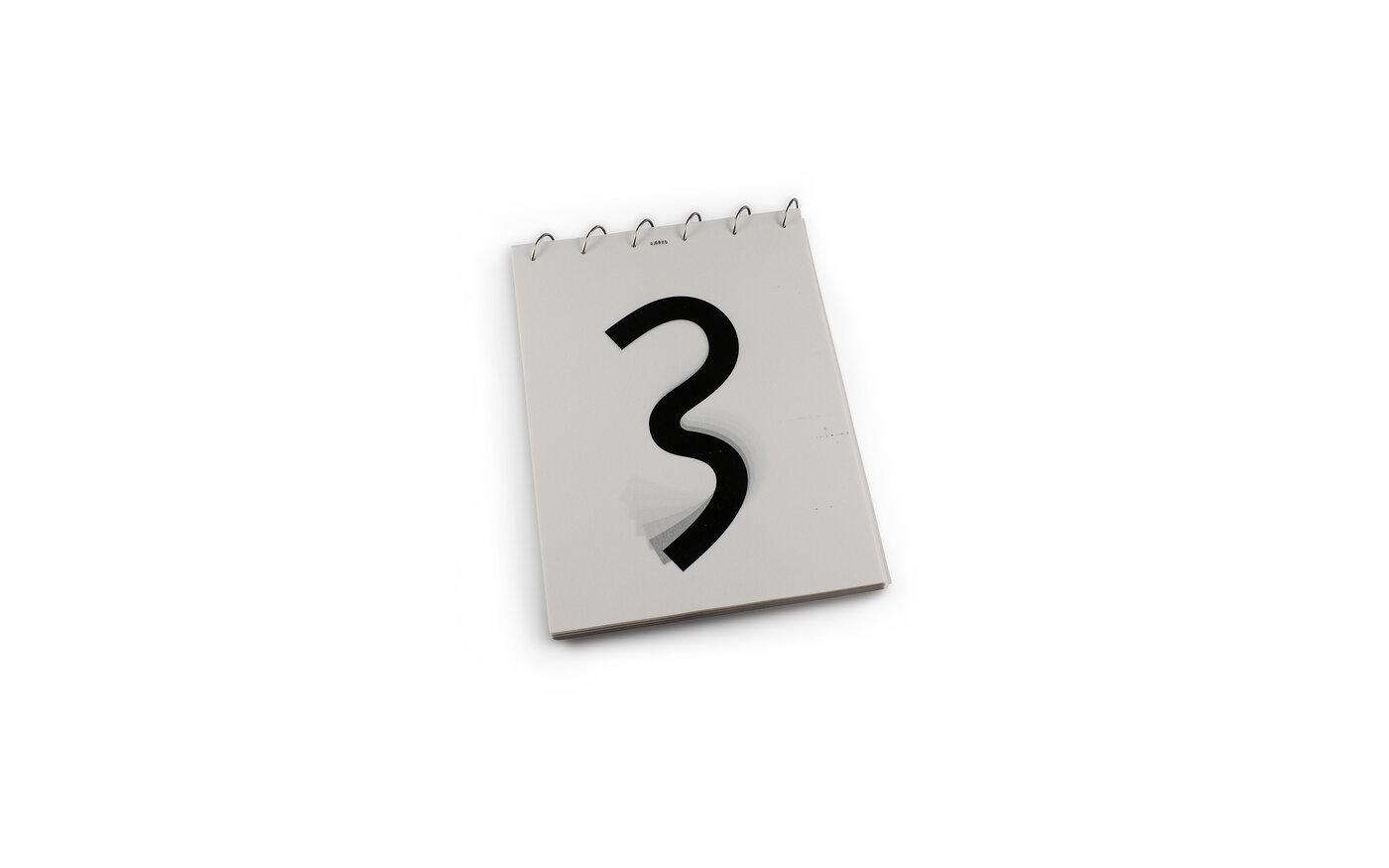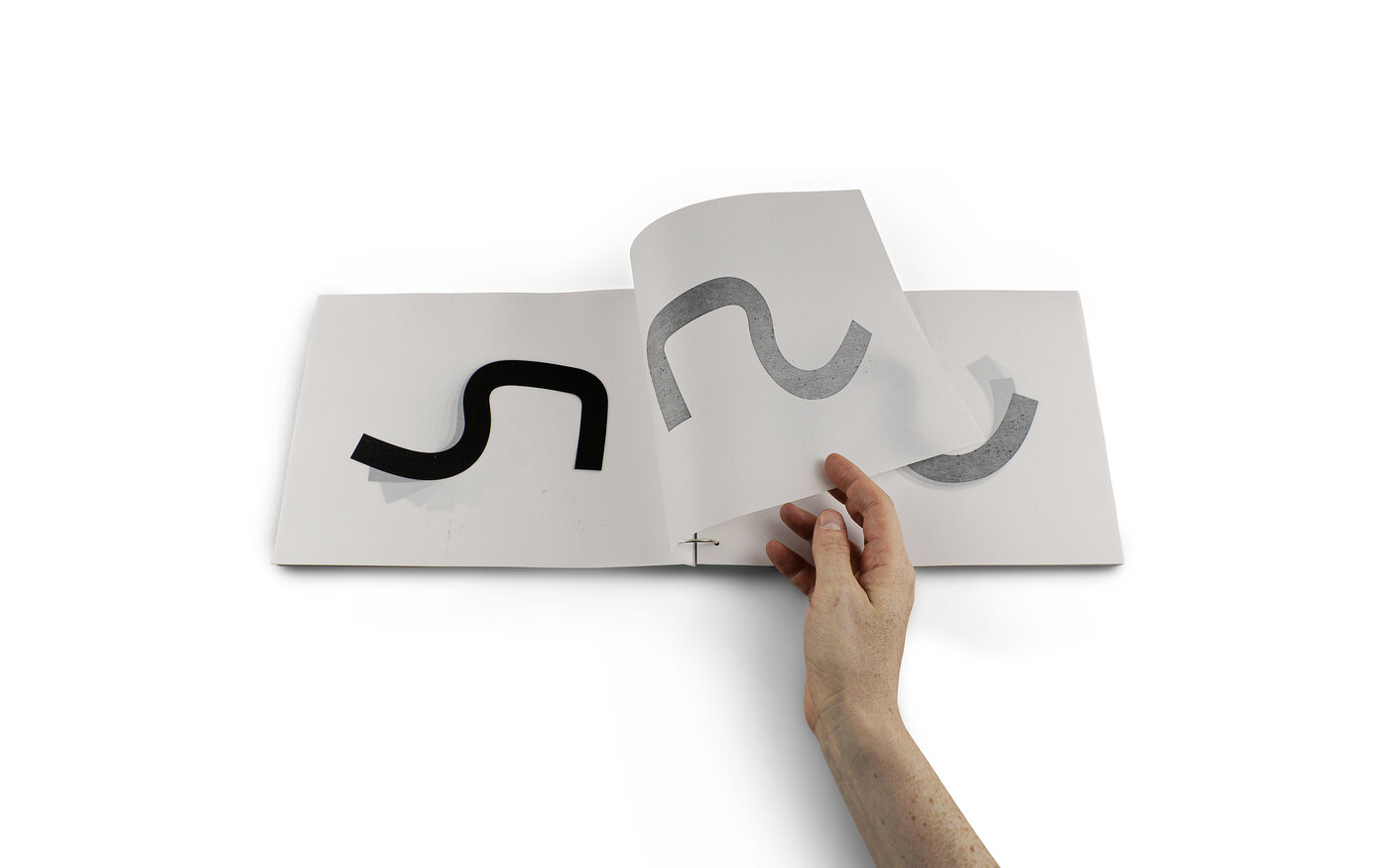
Eine Schriftart als künstlerische Arbeit: »variable-clock-font« ist eine Antwort auf die Frage, wie das aussehen könnte, was zwischen den Ziffern liegt, die die Zeit anzeigen. In ihrer Form als animierte Uhr macht die Arbeit das Ticken der Zeit zu einem Fluss. Hier wird dieser Fluss nun in den Raum des Buchs gebracht: Auf jeder sechzehnten Seite finden wir eine uns bekannte Zahl von 0 bis 9. Auf dem Weg zur nächsthöheren Zahl blättern wir durch Zeichen, die nicht mehr oder noch nicht als Ziffer zu erkennen sind. Das Transparentpapier, auf das sie gedruckt wurden, lässt den Verlauf der Formen erkennen. Wie die nahtlosen Ringe, mit denen die einzelnen Blätter verbunden sind, hat diese Bewegung weder Anfang noch Ende – sie kann endlos wiederholt werden.
A typeface as a work of art: variable-clock-font is a response to the question of what might lie between the shapes of the numbers that indicate time. As an animated clock, the work turns the ticking of time into a continuous flow. Here, that flow is brought into the space of the book: on every sixteenth page, we encounter a familiar digit from 0 to 9. On the way to the next, we leaf through forms that are no longer – or not yet – recognisable as numbers. Printed on transparent paper, we can trace their gradual transformation. Like the seamless rings binding the pages, this motion has no discernible beginning or end – it can be repeated over and over again.